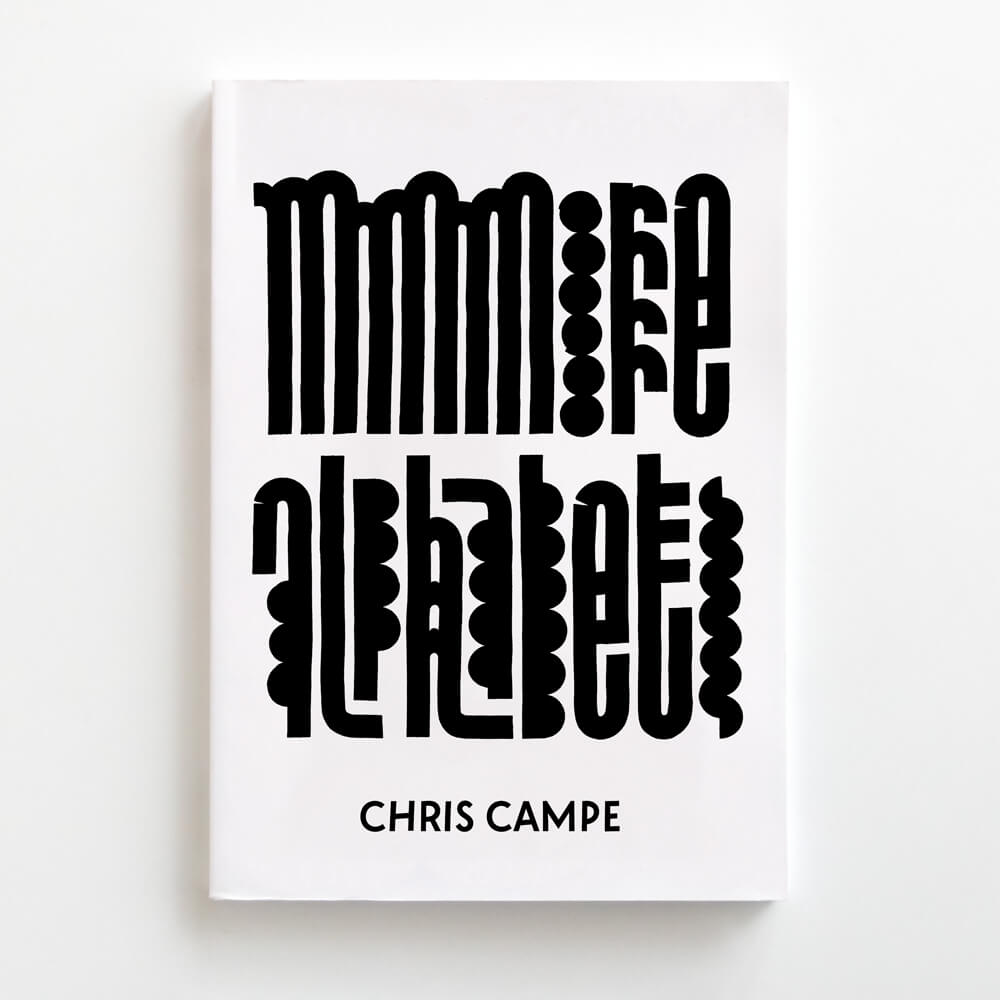
Sechs Wochen lang Schrift zeichnen mit individuellem Feedback und Austausch in einer kleinen Gruppe Gleichgesinnter. Das Ergebnis: eine eigene Herangehensweise an Schrift.
Als fokussierte Fortbildung oder for fun, als ausdrucksvoll-experimentelles Teambuilding oder kalligrafisch-meditativ und der mental health förderlich, als Schulung in Sachen Schriftwahl oder als Impuls über Trendfonts und Branding per Type.
Die Inhalte der Veranstaltung richten sich ganz nach den Interessen Ihres Teams und auch das Format ist flexibel: vom 30-minütigen Lunch-Talk bis zum mehrtägigen Praxisseminar.
Schrift ist eine Konvention: eine Übereinkunft darüber, welches Zeichen für welchen Laut steht. Zwei Senkrechten mit einer Horizontalen auf halber Höhe sind ein H, zwei Diagonalen mit einem Querstrich ein A – die Struktur der Buchstaben bleibt immer gleich, aber ihr Aussehen lässt sich unendlich variieren.
In diesem Workshop loten wir die Grenzen der Lesbarkeit aus. Mit Zeichenspielen und Experimenten untersuchen wir, was Schrift ausmacht. Wir untersuchen an welchem Punkt entfernen Buchstaben sich so weit von der Schriftkonvention entfernen, dass sie zu abstrakten grafischen Formen werden. So gewinnen wir einen frischen Blick auf das gewohnte Alphabet und Ideen für interessante Variationen.
Am Abend vorher, 19. Mai 2026 um 19 Uhr halte ich im WEI SRAUMforum einen Vortrag mit dem Titel Mit Absicht per Zufall – Schrift gestalten mit Offenheit und Haltung.
Letterforms are both text and image. Before we read a text, we perceive it visually. In this workshop, you will learn how to connect the shape of letters with the meaning of words to leverage the potential of lettering to communicate visually and verbally at the same time.
I will introduce you to the parameters that define the shape of letters and how they can systematically use these parameters to design custom letterforms that express exactly what they want to convey.
Am Tag vor dem Internationalen Frauentag malen wir Demoschilder für Gleichberechtigung, Solidarität und demokratische Teilhabe.
Zu Beginn des Workshops tauschen wir uns über politische Anliegen aus und sammeln Ideen für Formulierungen, die griffig und vielleicht sogar witzig auf ein Demoschild passen. Dann probieren wir aus, in welcher Form die Botschaften gut zur Geltung kommen und setzen diese mit Pinsel und Acrylfarbe um.
Am Ende haben alle ihr eigenes Schild und sind bereit für die Demonstration zum 8. März. Optional können die Workshop-Teilnehmer:innen am nächsten Tag gemeinsam an der Demonstration teilnehmen.